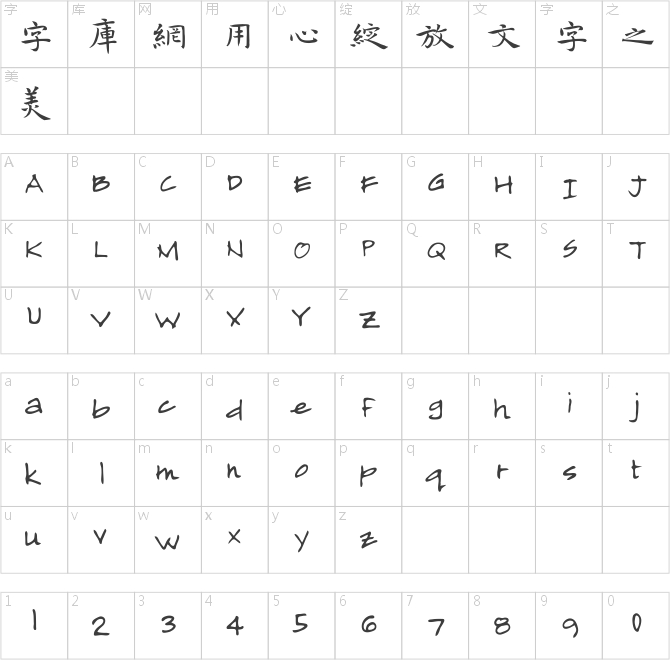
五臺(tái)楷書(shū)
李璜之
楷書(shū)
五臺(tái)楷書(shū),由“生活禪”先行者本覺(jué)上人在五臺(tái)山修持時(shí)主導(dǎo)設(shè)計(jì)、制作的一套楷書(shū)字體。集體成庫(kù),發(fā)行流通,惠施大眾,同品禪韻。 五臺(tái)楷書(shū),溯源于禪心,師法于禪門(mén)機(jī)鋒古趣,含八大山人之瀟灑自在;俱弘一法師之圓融潔凈。顯修證者抵心源之寂寂,涌自性之妙趣!以禪入墨,似本覺(jué)朗照之孤明無(wú)際;以墨寫(xiě)心,如流芳大千之妙用恒沙!五臺(tái)楷書(shū),細(xì)細(xì)品之,似文殊持慧劍斬絕翳穢,如觀音灑甘露普施清涼,滌人心肺,濾人思緒。